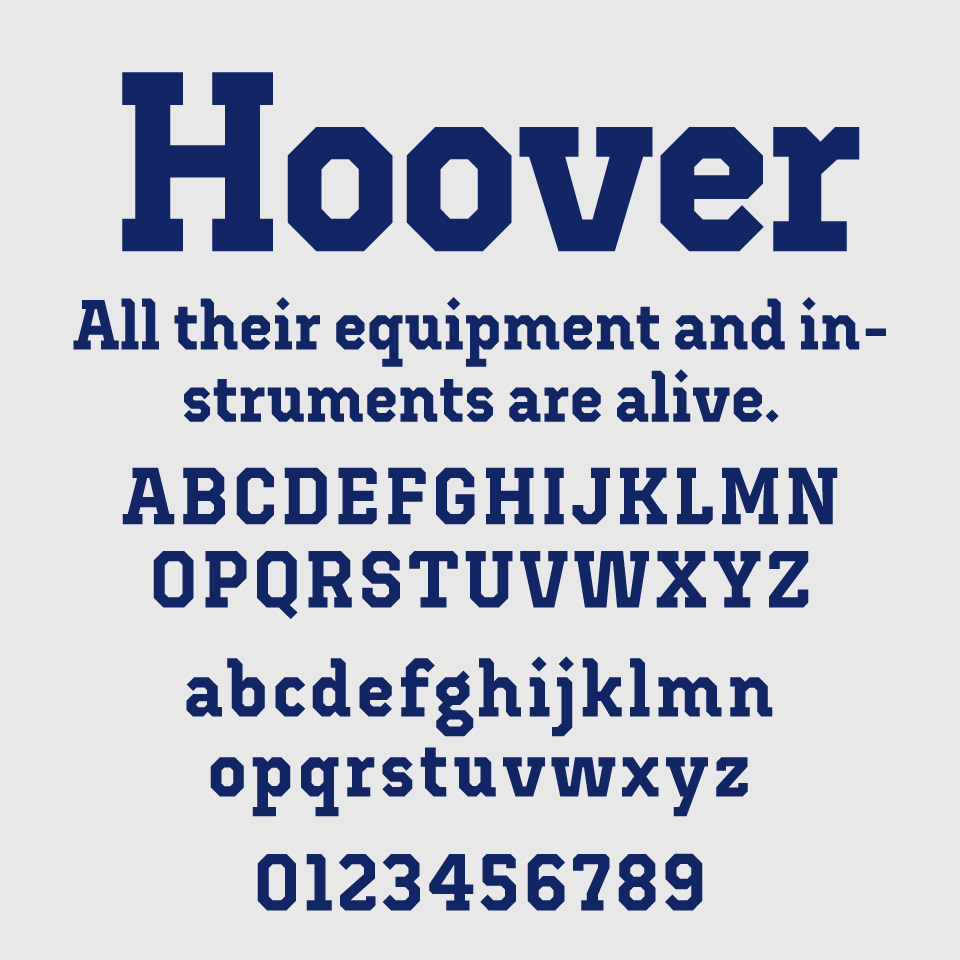
Hooverフォントは、がっしりとしたスラブと角ばったフォルムが、堂々たる存在感のあるスラブセリフ体フォントです。
大文字のどっしりとした佇まいに対して、小文字は丸みがあり、無骨さの中に少しだけ親しみも感じられるバランス感が魅力です。
大学のスポーツロゴやアメカジ系のブランドを彷彿とさせ、力強さと信頼感を伝えるスポーティなデザインがとても素敵です。どこか古き良きアメリカンな空気をまとった、頼りがいのある印象を持つフォントです。